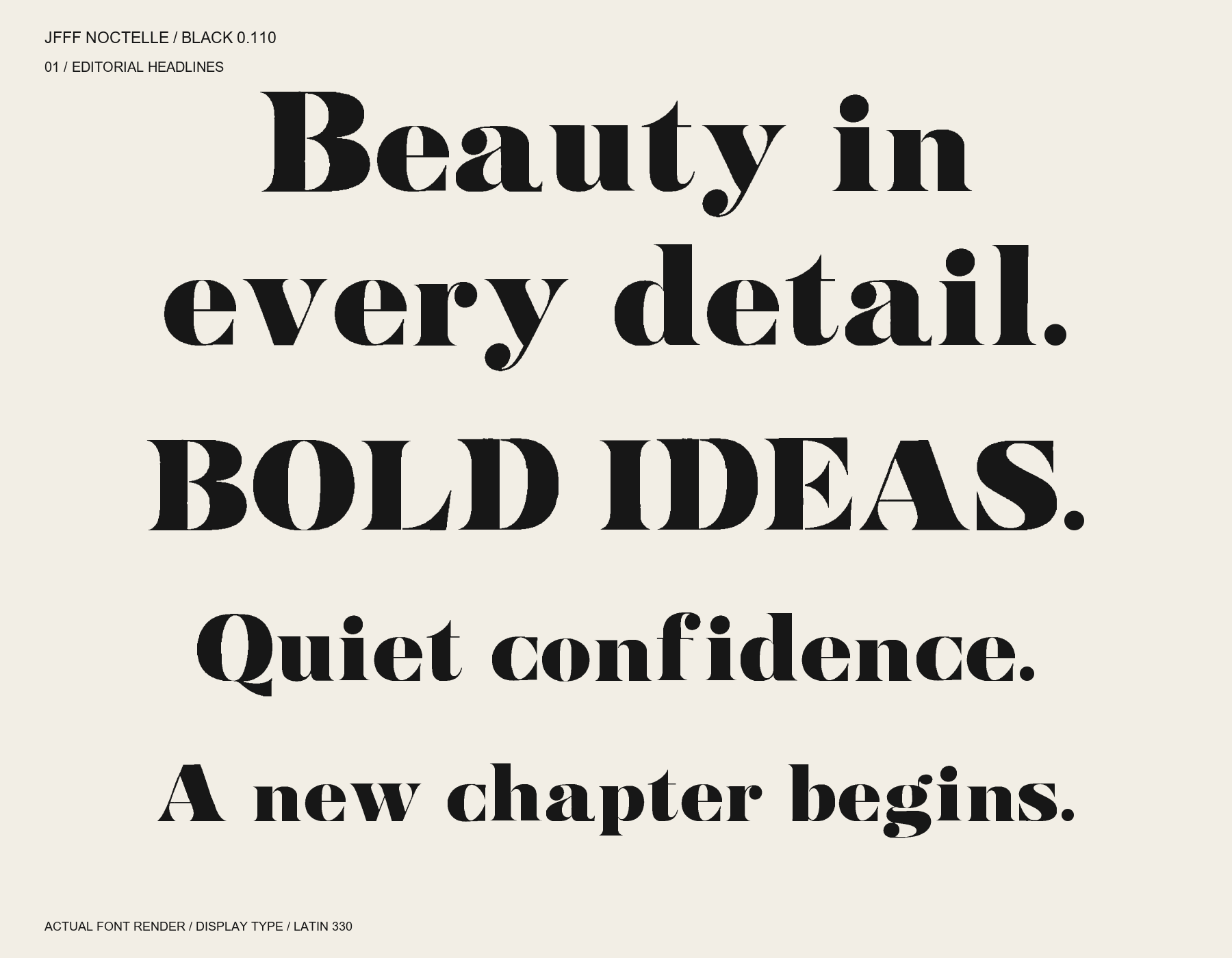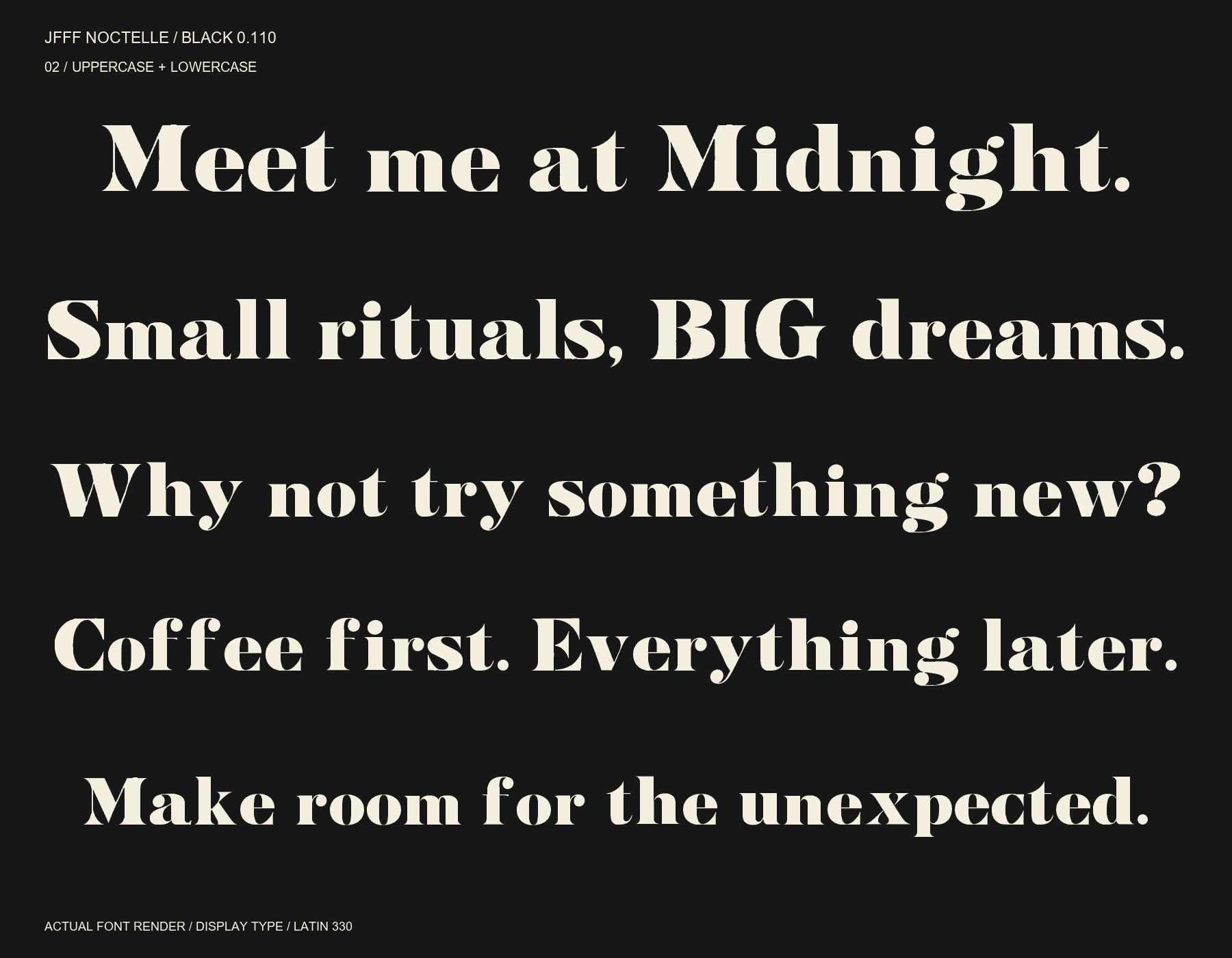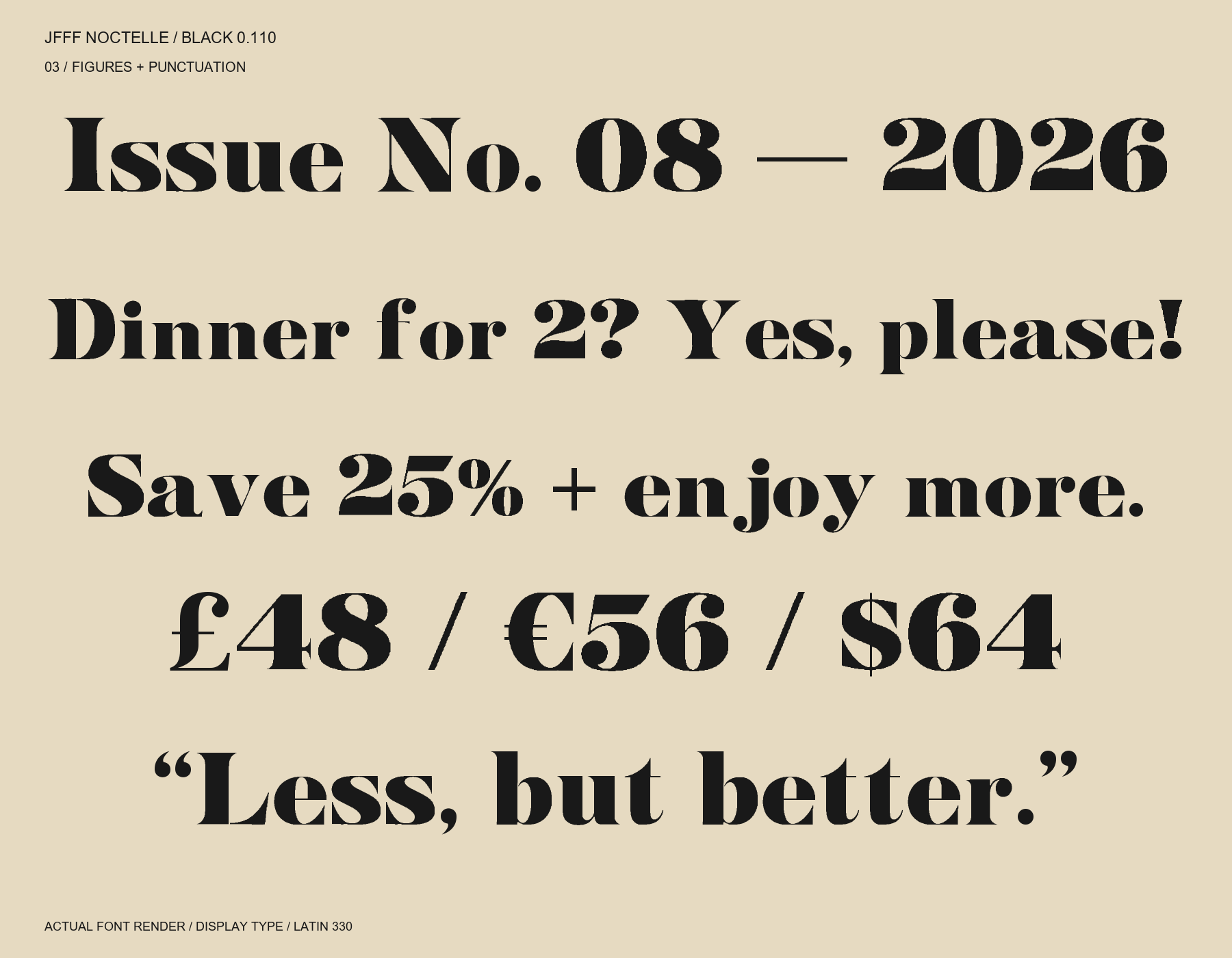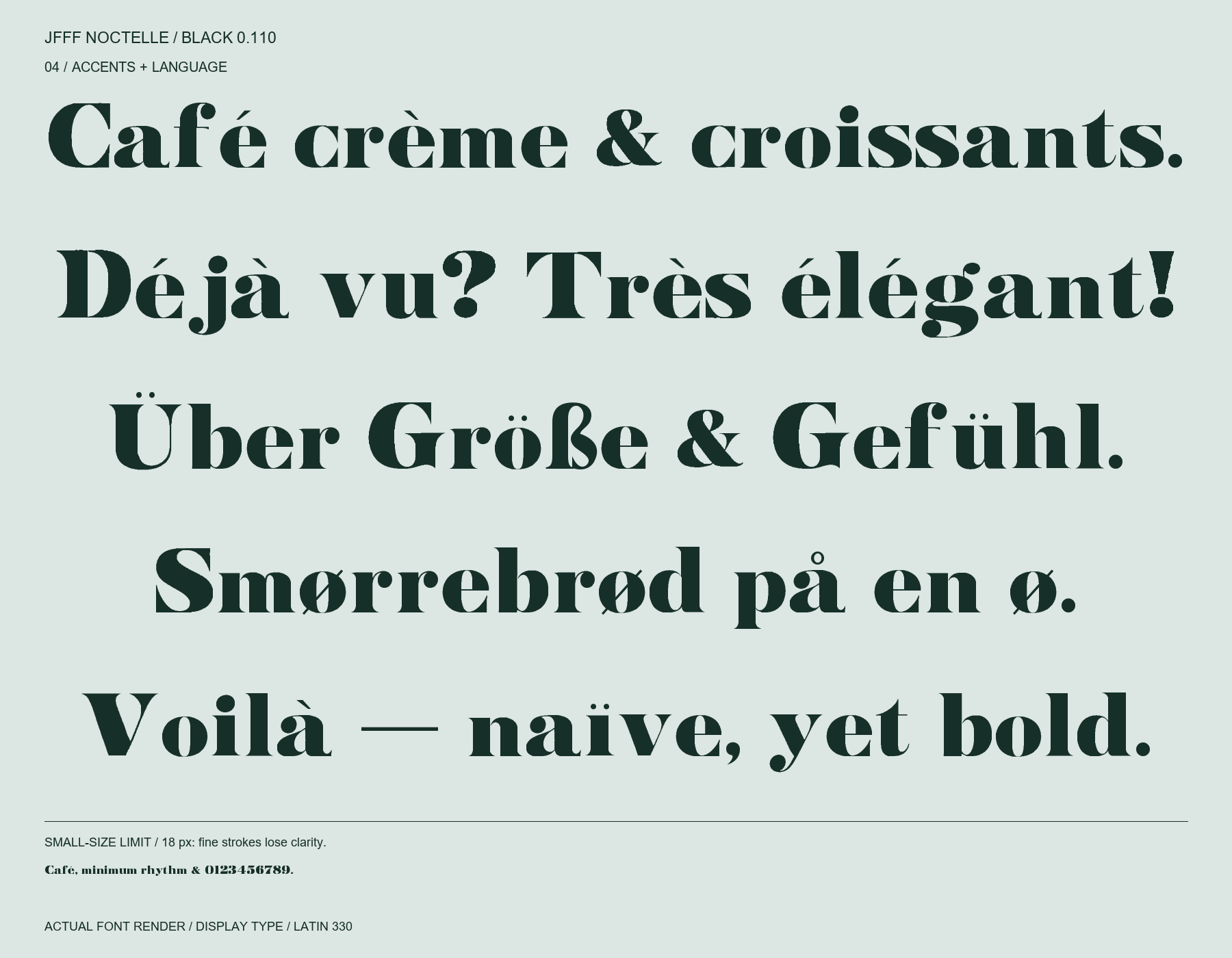
Free high-contrast serif font
Latin only. No Hangul.
Noctelle는 굵은 세로획과 섬세한 가는 획, 날카로운 세리프, 좁고 긴 타원형 속공간이 특징인 직립 디스플레이 서체입니다. 공 모양 끝맺음과 두 층 구조의 a·g가 고전적인 인상을 더합니다. Black 0.110 · 라틴 330자(공백 2개 포함). 영문 대소문자, 숫자, 라틴 확장 문자와 문장부호·통화·연산 기호를 지원합니다. 한글과 독립 결합 악센트는 포함하지 않습니다. 330자 확대 시트를 검수하고 높이, 악센트, 확장 문자와 기호를 조정했습니다. 미세 윤곽 정리를 포함해 231자의 윤곽이 변경되었습니다. 72px 이상 큰 제목, 포스터와 편집 디자인에 권장합니다. 작은 본문에서는 가는 획의 가독성이 떨어질 수 있습니다. 0.x 초기 버전이며 인쇄, macOS 및 전체 문자쌍 커닝 검증은 완료하지 않았습니다.